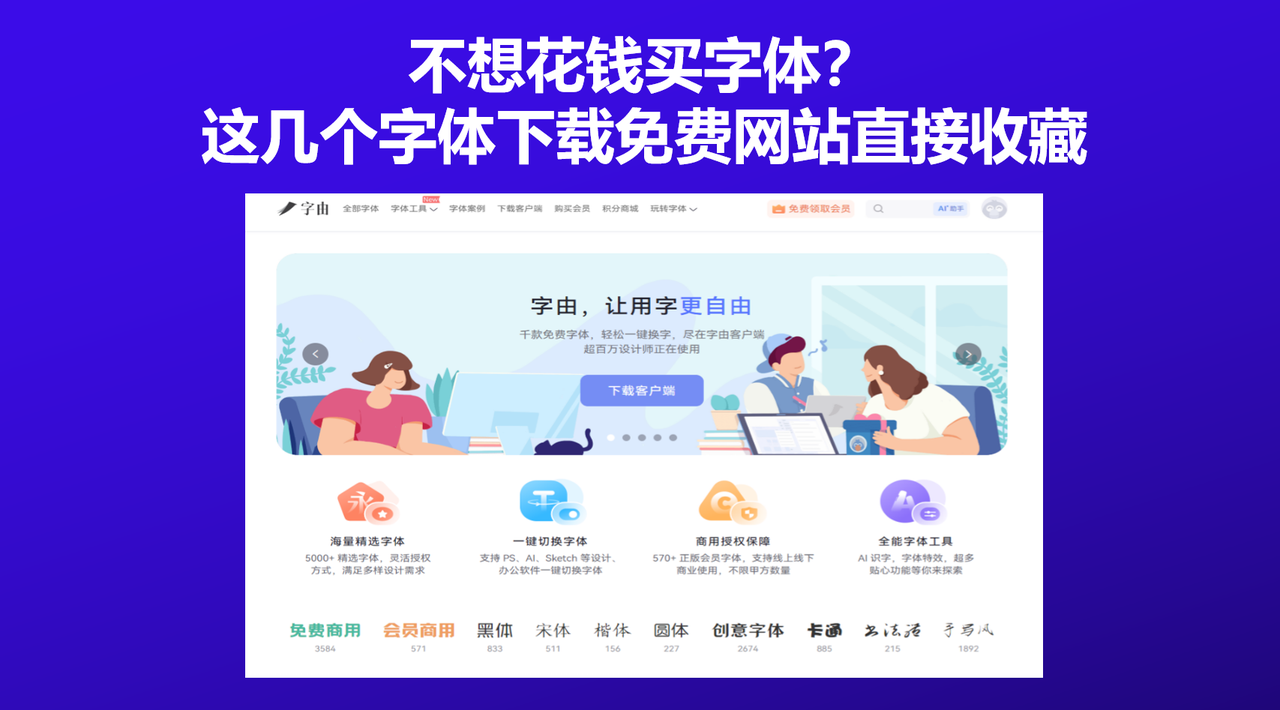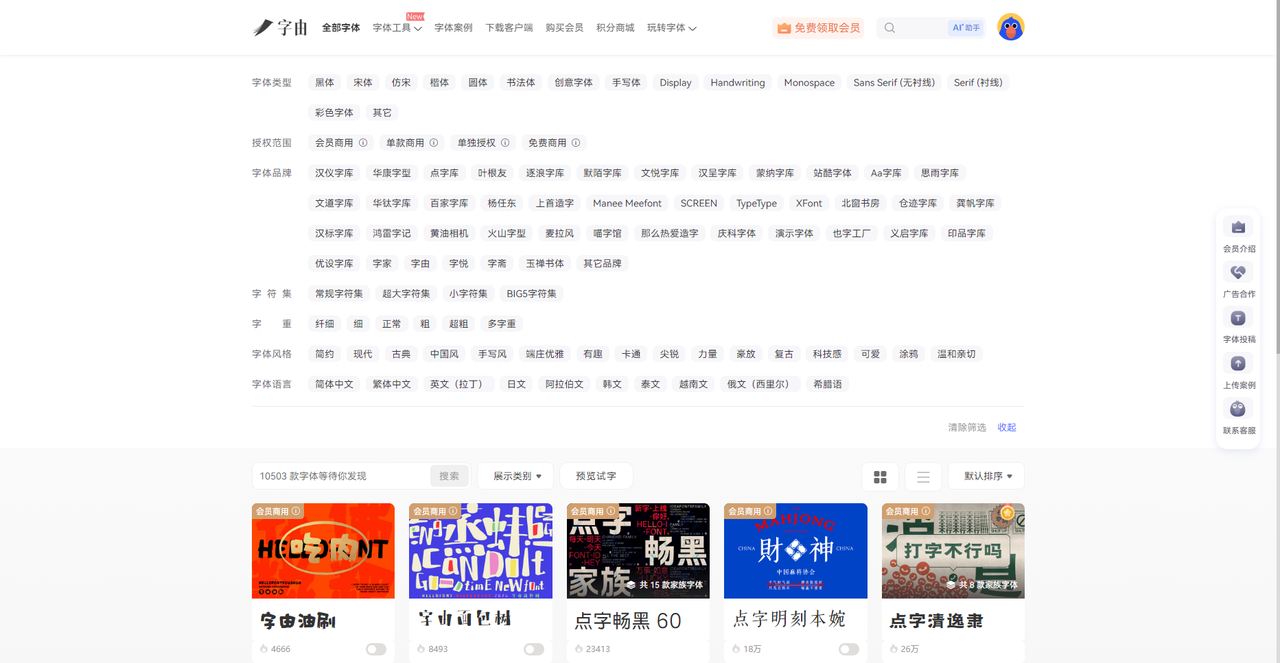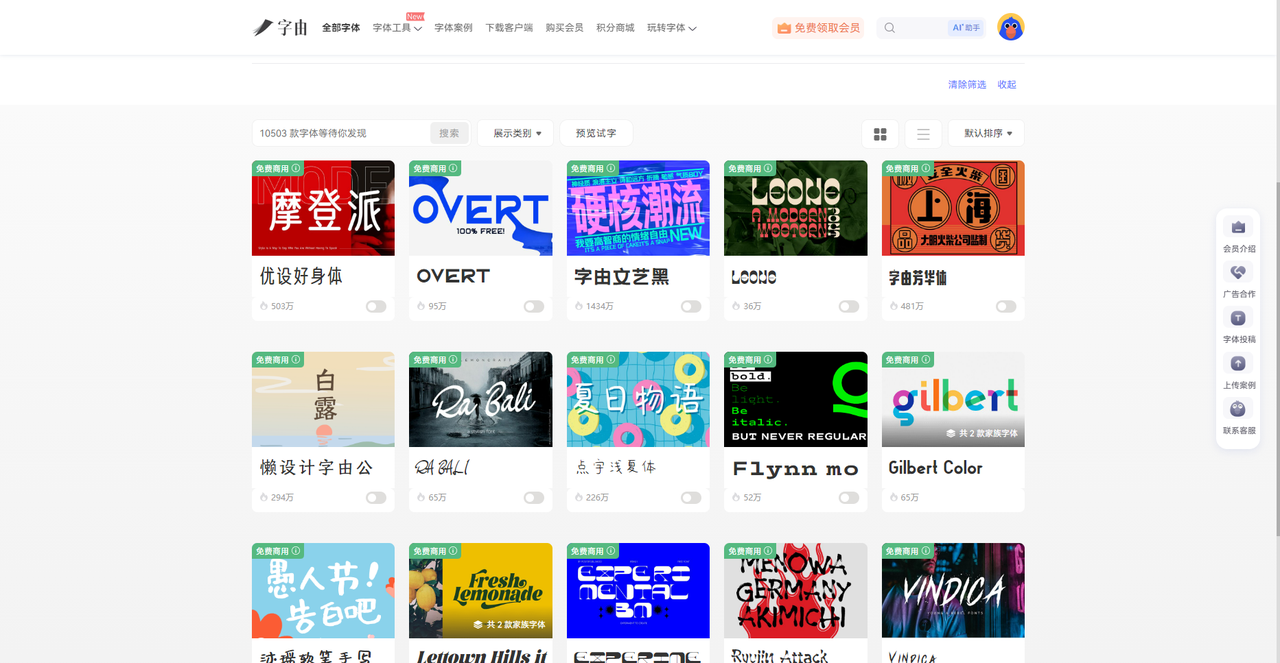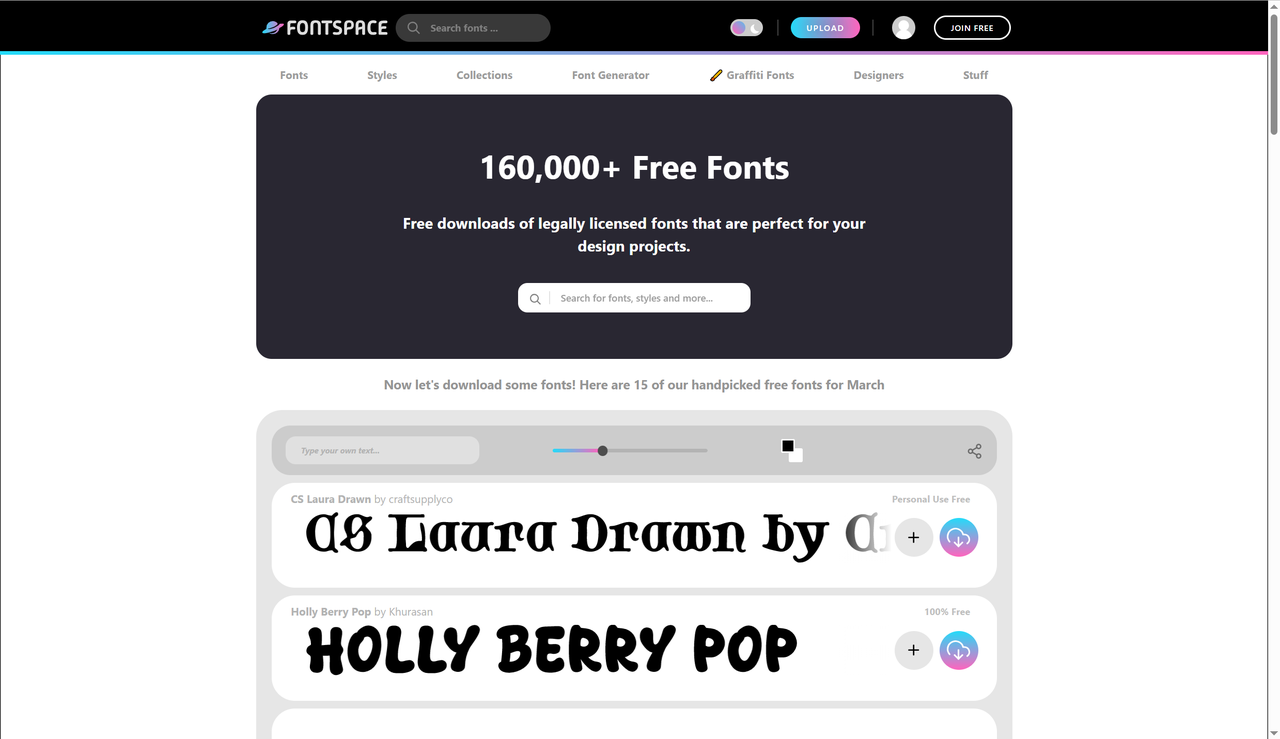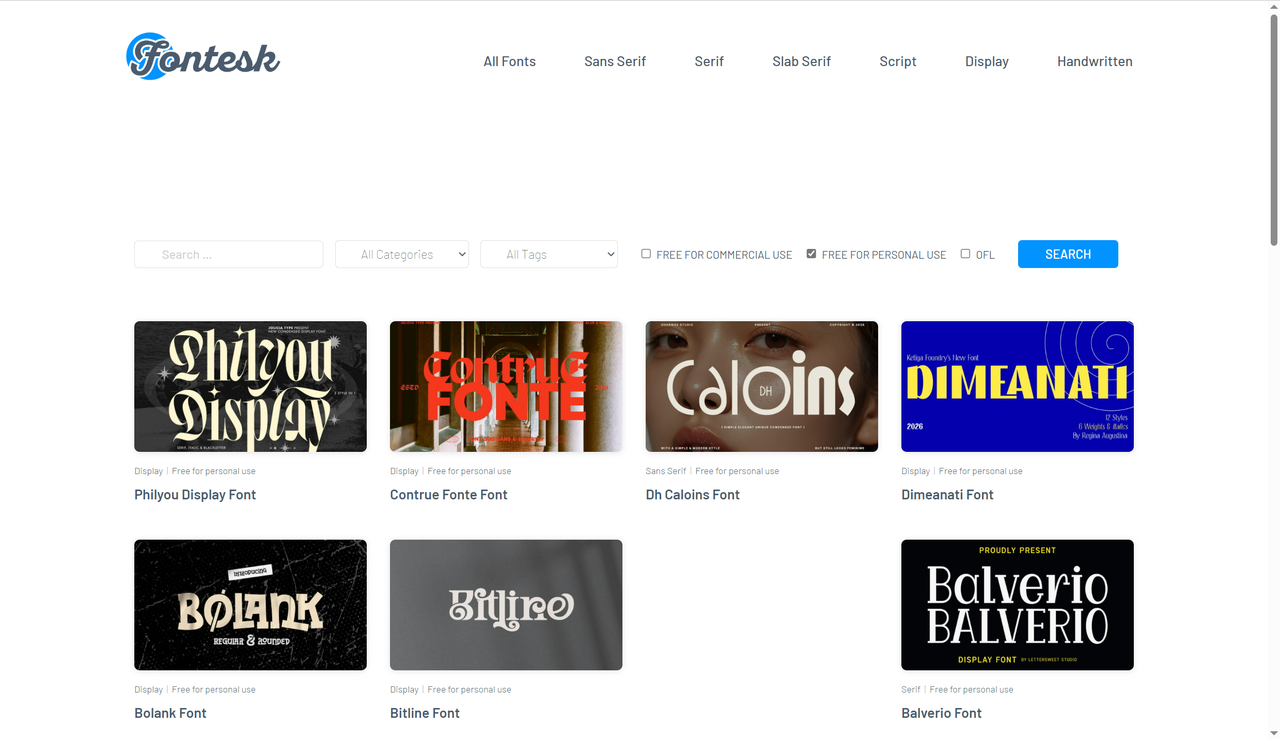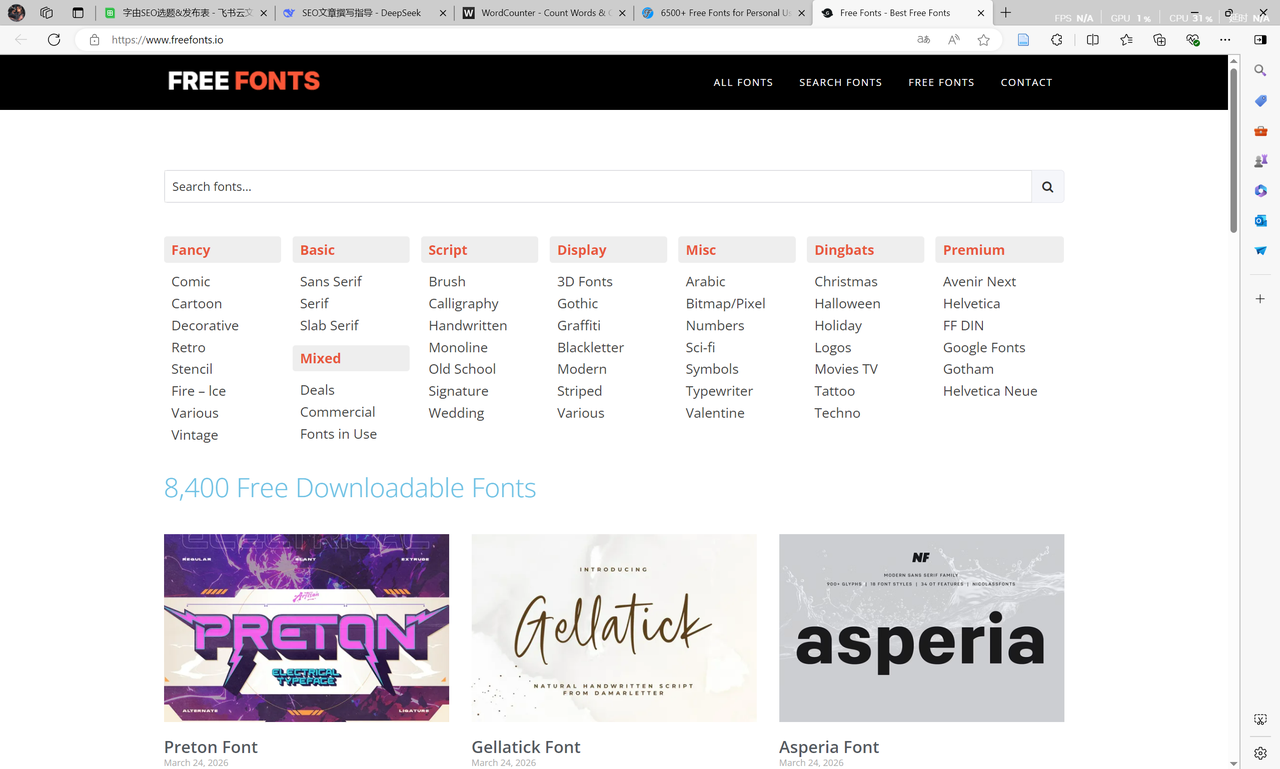
不想花钱买字体?这几个字体下载免费网站直接收藏
好看的、实用的字体实际上是需要长期积累出来的,不论是自己花费时间去网站海底捞针搬找适合设计的字体,还是下载别人现成的字体包,都是积累的方式。但是时间长了,设计的水平提高了,你自然会需要一些质量更高的需要付费的字体。但是就是有这样一些网站,能够在保证字体质量的同时还能够做到免费和可商用,那么今天我就把私藏的4 个字体下载免费网站一次性分享出来,每一款都是可以免费下载字体、授权类型清晰的字体网站,需要的可以收藏。
第一个要推荐的字体下载免费平台是字由。很多人知道字由是字体管理神器,但它本身就是一座巨大的免费字体库。目前字由收录了超过10500 款字体,其中3585 款是免费可商用的。这个体量意味着什么?就是你日常设计需要用到的黑体、宋体、书法体、手写体、艺术体,基本都能在这里找到,而且全部标注了授权类型,用着放心。
关于怎么在字由快速找到可商用的免费字体:
字由的筛选功能非常强大。点开“全部字体”,上方有详细的筛选栏(如果你是网页版的话):
• 按类型:黑体、宋体、书法体、手写体、Sans Serif、Serif等
• 按热度:每款字体右下角有使用次数,优先选热度高的
• 按品牌:汉仪字库、蒙纳字库、Aa字库等官方合作品牌专区
除此之外,字由里热度高又实用的免费字体不少,我会挑几款自己常用的推荐给大家:
• 优设好身体:字形方正饱满,适合正文排版、画册配文
• 字由文艺黑:既有黑体稳重又带手写感,适合标题、海报
• 字由芳华体:温柔手写风,适合文艺类设计
• 优设标题黑:方正有力,适合电商主视觉
• 思源黑体 Medium:经典开源字体,适合UI界面
• 江西拙楷:朴拙手写感,适合国风、文创设计
2、FontSpace
FontSpace 是一个老牌免费字体社区,它的首页写着“160,000+ Free Fonts”——16万款免费字体,是目前全球最大的免费字体库之一。这个体量意味着无论你想要什么风格,基本都能在这里找到。网站首页每月会推荐15款手选免费字体,比如“CS Laura Drawn”等。你可以按“NEW”、“POPULAR”、“RANDOM”、“COMMERCIAL-USE”等分类浏览,而且网站社区十分活跃,不用担心字体款式老等问题。
3、Fontesh
Fontesh 是一个分类非常细致的字体网站,它的“All Tags”里有“FREE FOR COMMERCIAL USE”和“FREE FOR PERSONAL USE”两个标签,帮你快速区分授权类型。这也是我用着最顺手的网站之一。目前我推荐的免费字体有:
• Shilou Display:Display风格,免费个人使用
• Contrue Fonte Font:Display风格,免费个人使用
• Dimeanati Font:Display风格,免费个人使用
• Bolank Font:Display风格,免费个人使用
每款字体都标注了授权类型和风格标签,方便快速筛选。Fontesh 的分类系统很强大,左侧有Sans Serif、Serif、Slab Serif、Script、Display、Handwritten等大类,每个大类下还有更细的标签。如果你想在海量字体里快速定位免费字体,这里很好用。
4、FREEFONTS
FREEFONTS 是一个巨大的字体下载免费平台,目前收录了8400款免费字体。上端分类栏极其详细:
• Fancy:Comic、Cartoon、Decorative、Retro等
• Basic:Sans Serif、Serif、Slab Serif、Monoline等
• Script:Brush、Calligraphy、Handwritten、Monoline等
• Display:3D Fonts、Gothic、Graffiti、Blackletter等
• Misc:Arabic、Bitmap/Pixel、Sci-fi、Symbols等
这种分类的好处是,你可以根据项目需求快速定位,比如说你想要比较优雅的字体,可以直接按标签来选,不用在一堆字体里盲目翻。每款字体都有预览图,下载前还能输入自己的文字试效果。虽然需要留意授权说明(有的免费商用,有的仅限个人),但胜在字体体量大。